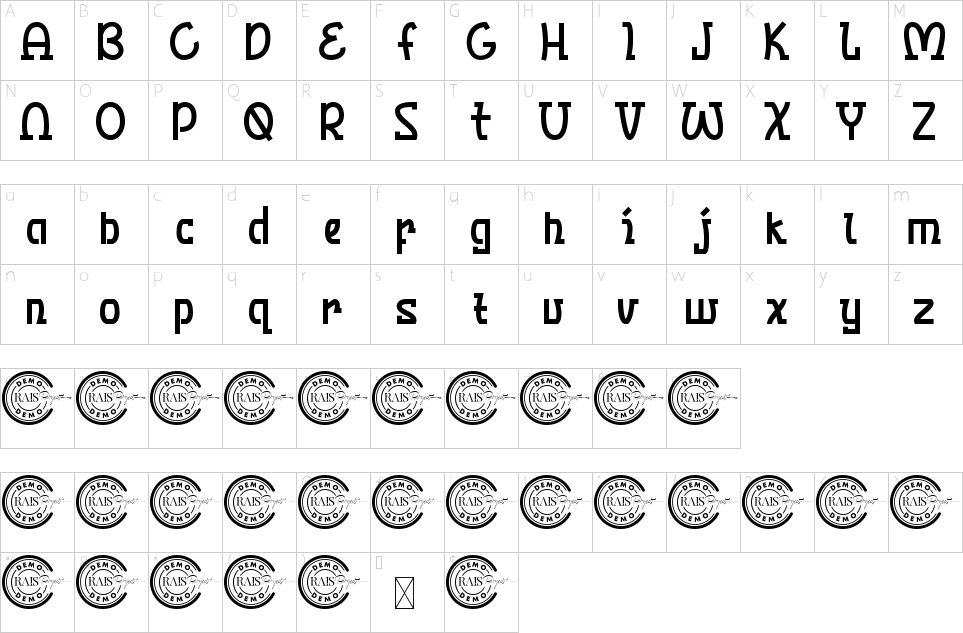
A fonte Mizunami oferece uma paleta de linhas suaves e modernas para seus projetos digitais, projetada pelo designer não informado. Com um design minimalista, Mizunami se torna uma opção versátil que combina perfeitamente em diversas aplicações, desde design gráfico até materiais de marketing digital. Se você está procurando uma fonte de graça para dar um toque único e elegante a seus projetos, Mizunami pode ser a escolha perfeita. Com 1,408 downloads no total, é uma fonte popular que atende a uma ampla gama de necessidades. Seja para um projeto pessoal ou uma produção de marcas, Mizunami é uma fonte que se adapta a qualquer formato.